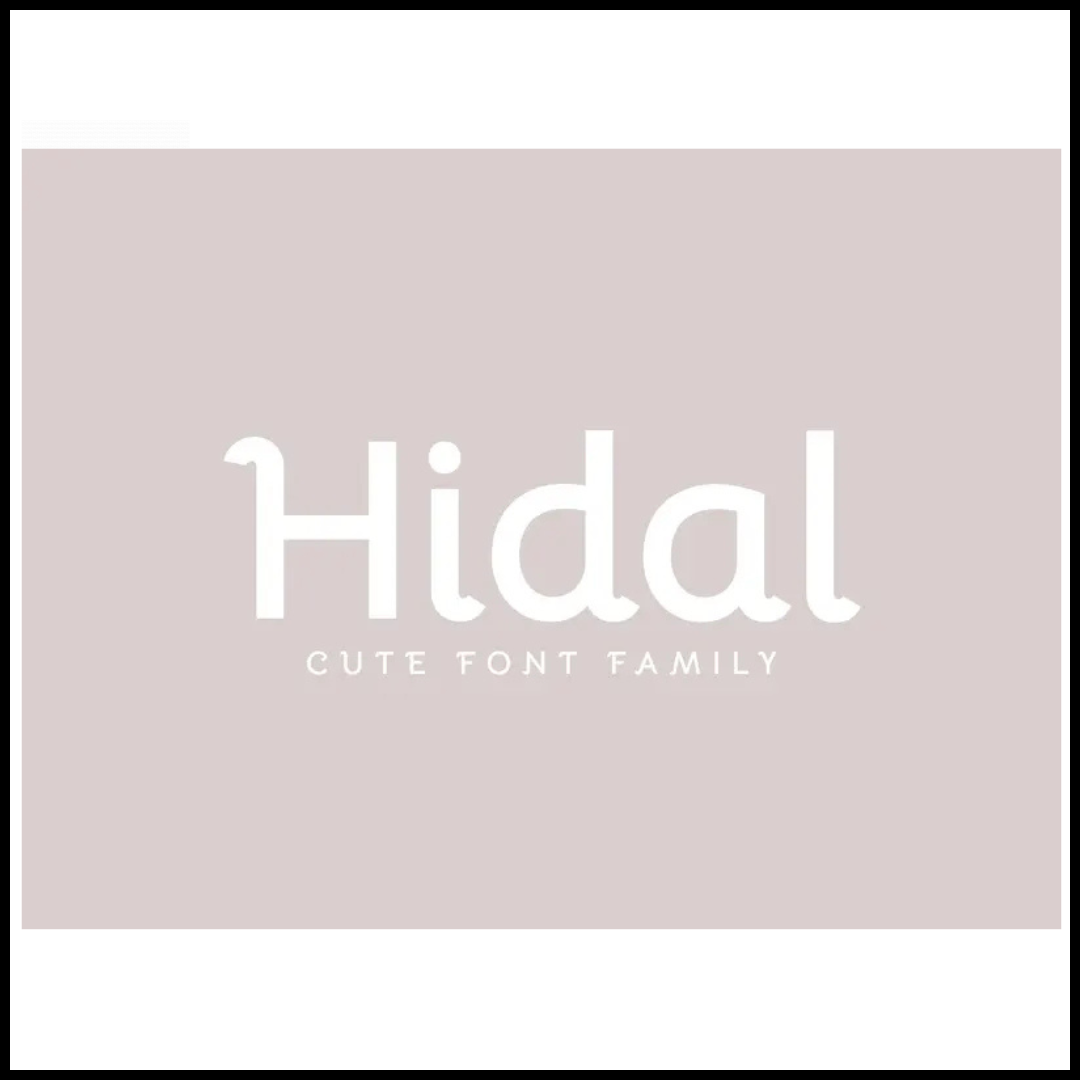
Sans-Serif-Font-Family
???? Sans-Serif Font Family – الخط المثالي لتصاميمك العصرية
ارتقِ بأعمالك البصرية مع Sans-Serif Font Family، مجموعة خطوط أنيقة وعصرية مصممة لتمنح تصاميمك لمسة احترافية ووضوحًا بصريًا استثنائيًا.
تمتاز هذه العائلة من الخطوط بأسلوبها البسيط والنظيف، مما يجعلها مثالية للاستخدام في الشعارات، واجهات المستخدم، العروض التقديمية، المحتوى الرقمي، والتصميم الطباعي.
لماذا ستعشق هذا الخط؟
✔️ وضوح عالٍ: تصميم هندسي دقيق يضمن سهولة القراءة على الشاشات والمطبوعات.
✔️ استخدامات متعددة: مناسب للهوية البصرية، الإعلانات، المحتوى الرقمي والمطبوعات.
✔️ تنوع في الأوزان: تتضمن العائلة عدة أوزان (خفيف – منتظم – سميك) لتناسب كل الاحتياجات.
اجعل كل كلمة تبرز بأسلوب أنيق ومحترف.